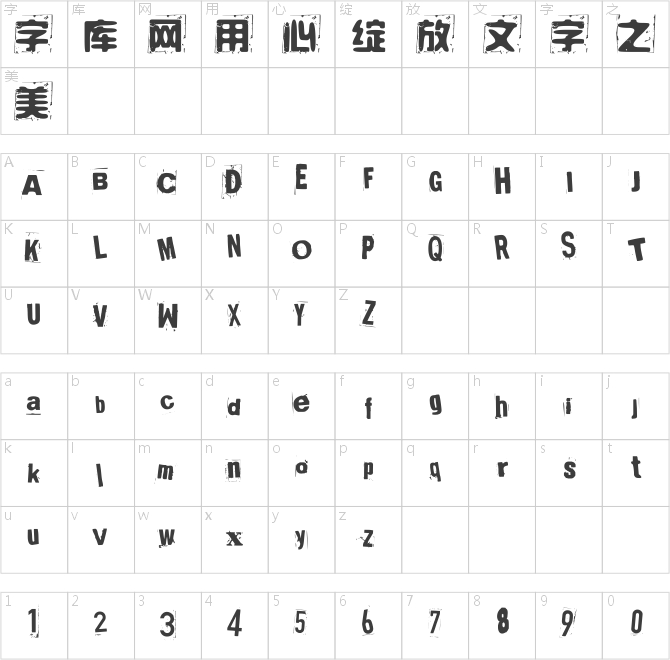
奇思古粗廢墟體 詳情頁
字體名稱: 奇思古粗廢墟體
奇思古粗廢墟體
奇思古粗廢墟體字體古粗廢墟字庫是一款讓人賞心悅目、百看不厭的中文字體,適合各類廣告和產(chǎn)品包裝設(shè)計(jì)應(yīng)用,字體大小14.31MB,格式為ttf字體,上傳用戶是Aa字庫,作者/版權(quán)方為奇思字庫